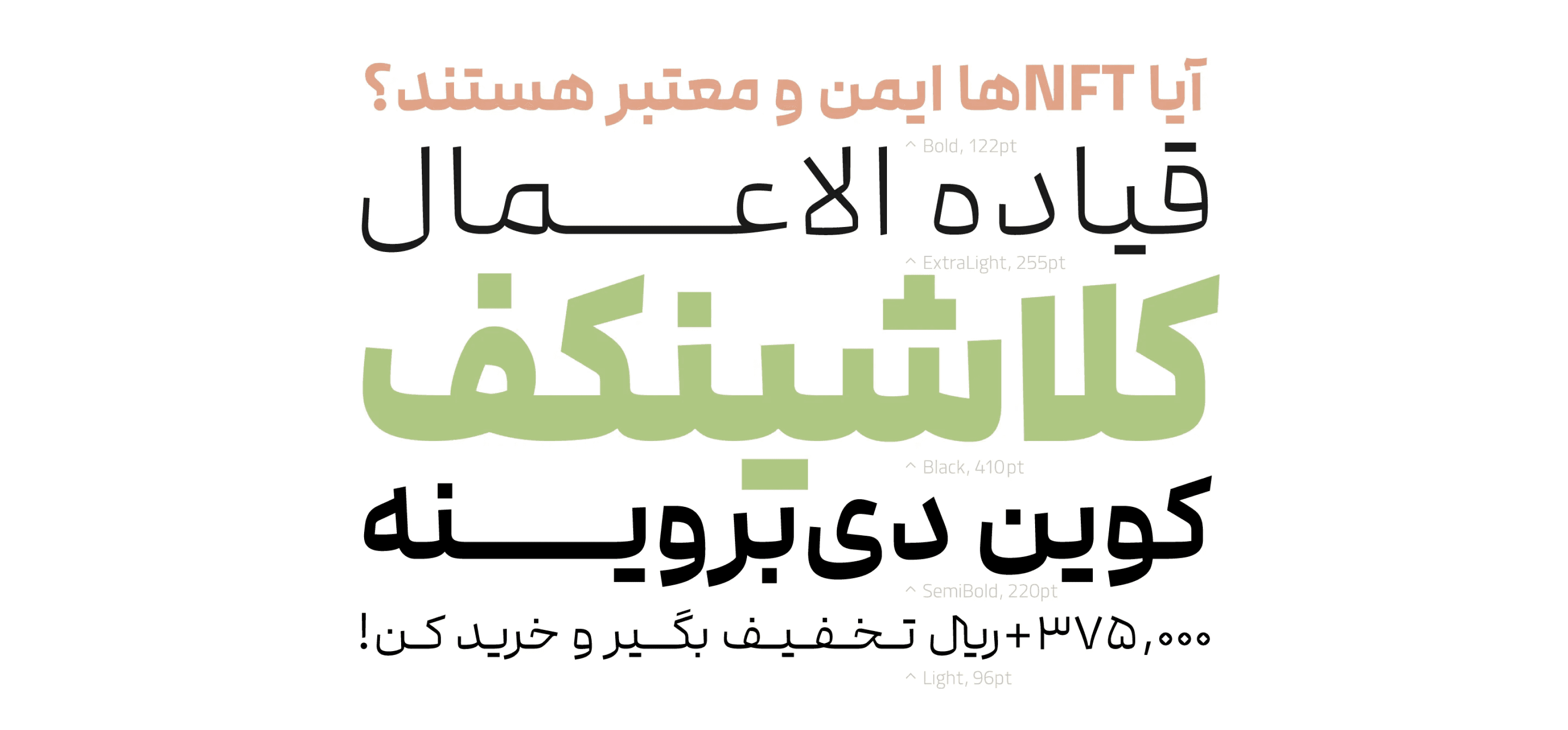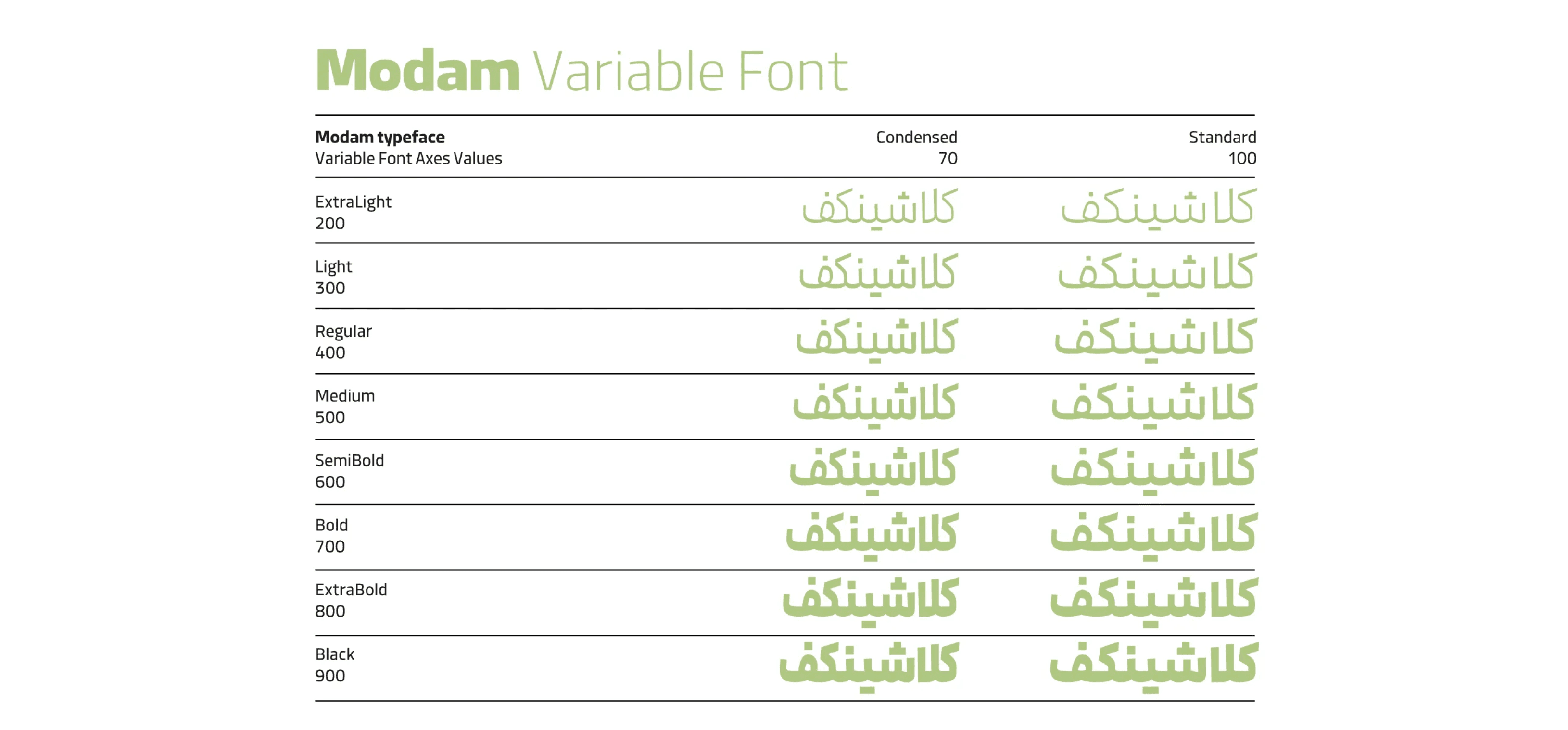
يتميّز خط Modam ببنية بسيطة، وعناصر هيكلية واضحة، ومساحات سلبية مفتوحة.
وبفضل طابعه التعبيري ونسبه الهندسية الدقيقة، يُعد هذا الخط مناسبًا للعناوين والنصوص القصيرة إلى المتوسطة، حيث يجمع بين الوضوح البصري والطابع المعاصر.